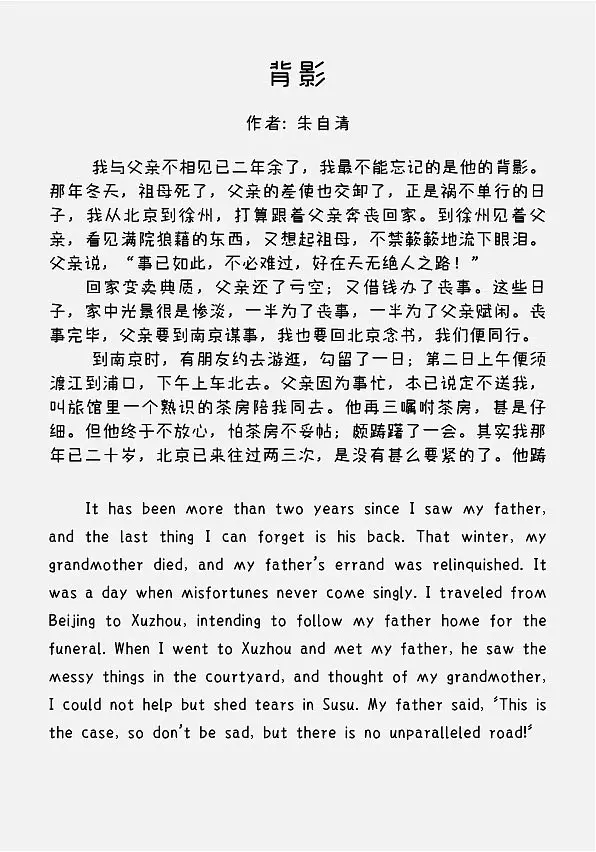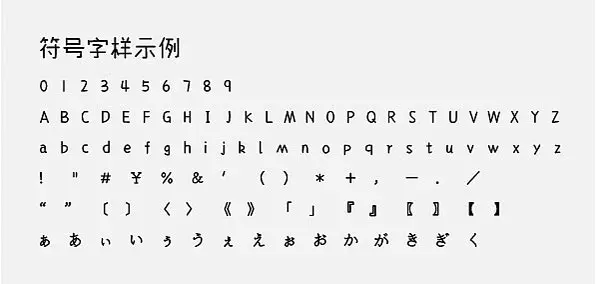
2022年,我們將精力始終如一的放在這款字體上,無論是質量還是數量,我們團隊都非常有信心它可以帶給大家更有趣、更豐富的使用感受。
我們將這套字體取名“字幫玩酷體”,像名字一樣,它的字形風趣,筆畫多元,字形錯落有致,風格輕鬆玩趣,收錄GBK編碼共20923個文字及987個符號,滿足各種使用場景。相信大家在打一些生僻字時會有“被默認”的情況,字體很難統一,但字幫玩酷體無論是常用字還是生僻字都不會讓大家有這樣的煩惱。